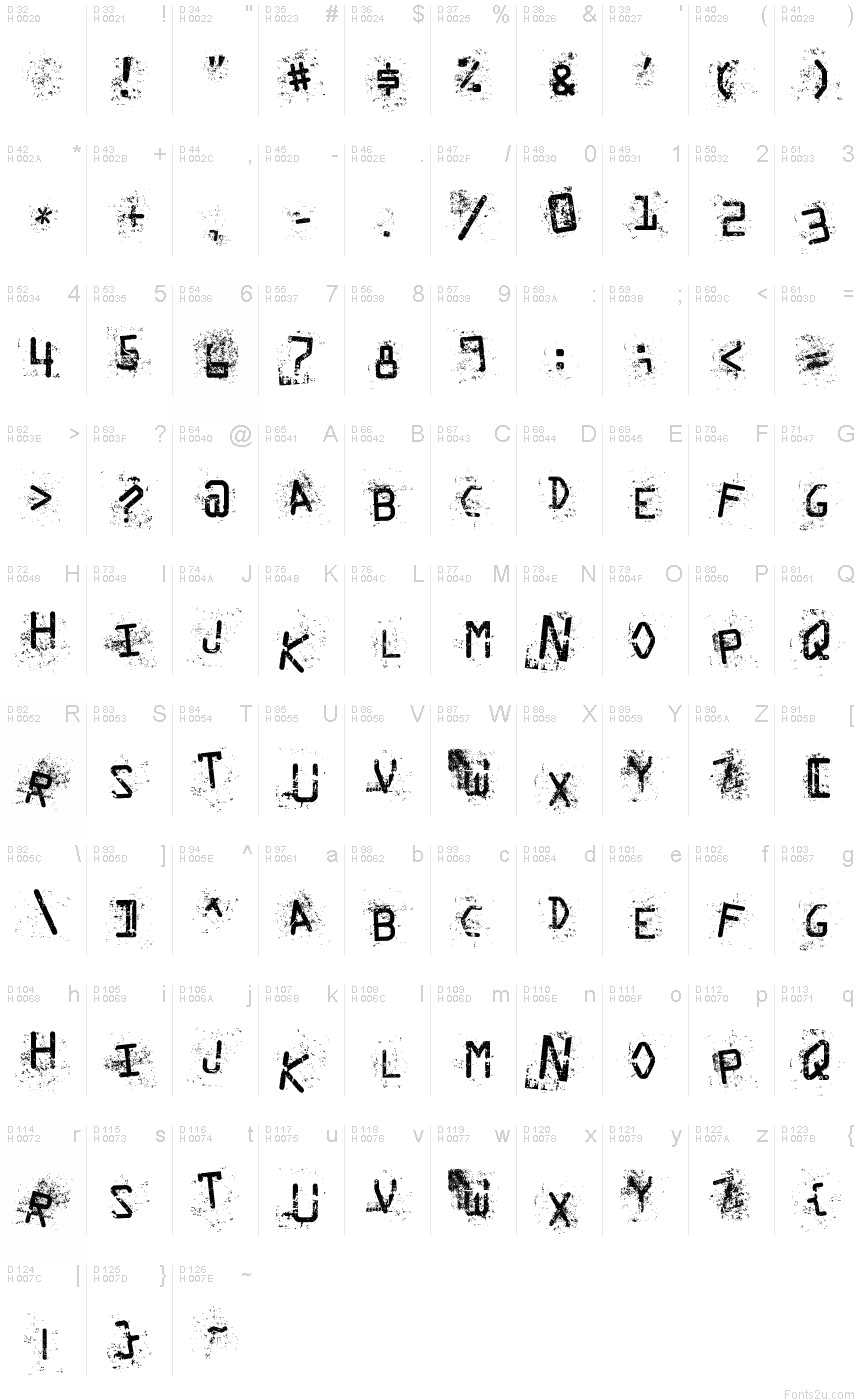
Staubiges Vergnügen
Staubiges Vergnugen od Nihilschiz Fonts to bezpłatny krój display typu 'distressed' z surowym, plakatowym charakterem. Litery wyglądają na zdrapane, poplamione i nieco nieokiełznane, jakby odciśnięto je na brudnym murze i zostawiono na pastwę pogody – a mimo to wyraziste, pogrubione wielkie litery sprawiają, że ten chaos wygląda na w pełni zamierzony.
Idealnie pasuje do ulotek klubowych, okładek zinów, plakatów zespołów, tytułów i surowego brandingu, gdzie czystsza typografia wydawałaby się zbyt grzeczna. Jako bezpłatny font sprawdza się najlepiej w krótkich formach – dużych nagłówkach, okładkach czy inicjałach – ponieważ to właśnie poszarpana tekstura i nieregularny rytm grają tu pierwsze skrzypce.